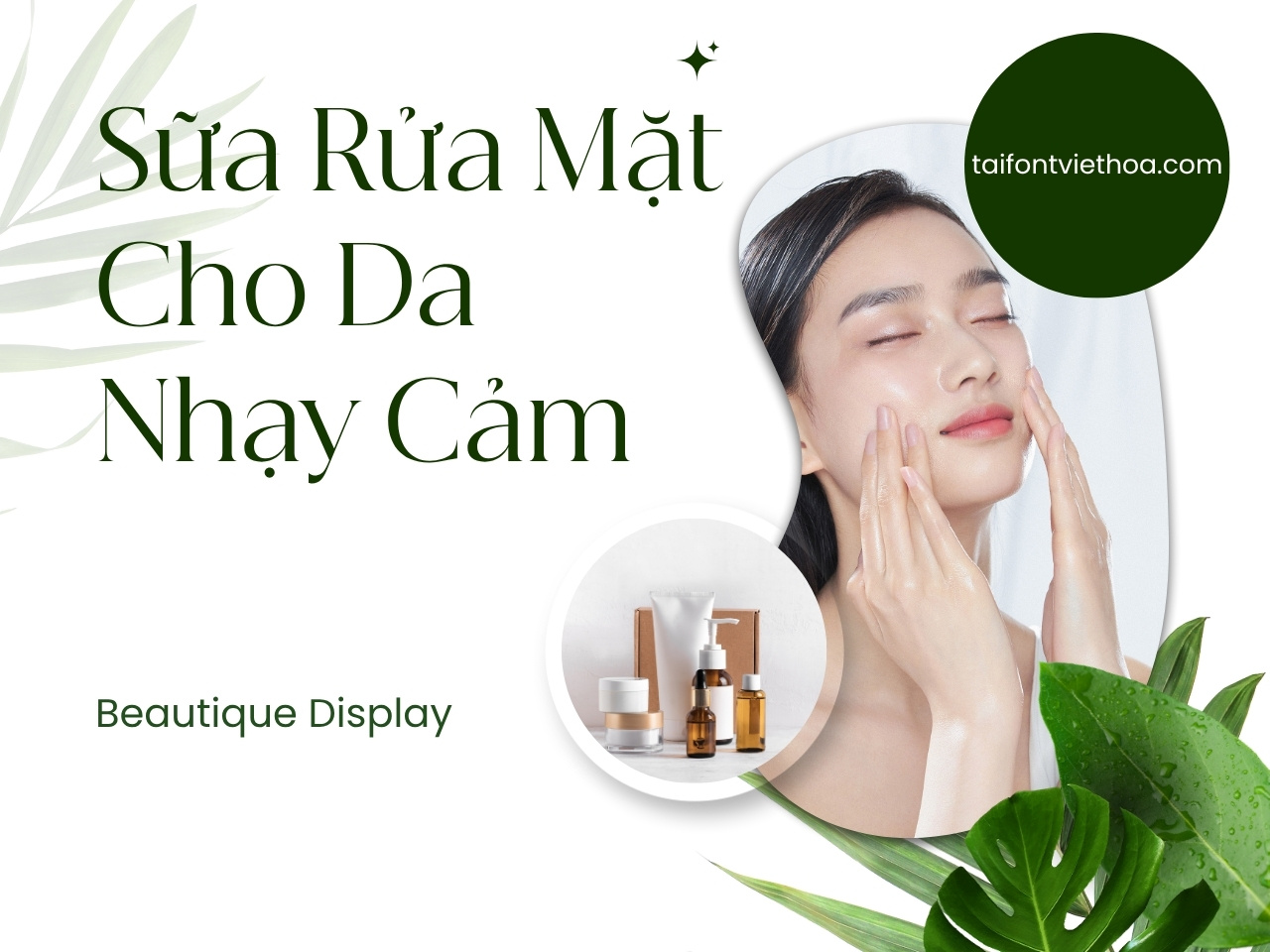
Giới thiệu về font Beautique Display 1.1 và phiên bản Việt hóa
Beautique Display 1.1 là bản mở rộng nâng cao từ font Beautique Display – một thiết kế serif tinh xảo được phát triển bởi Beautype Studio. So với bản đầu tiên, phiên bản 1.1 được tinh chỉnh lại tỷ lệ chữ, mở rộng thêm bộ glyphs đặc biệt, đồng thời cải thiện khả năng hiển thị trên các thiết bị kỹ thuật số và in ấn. Font vẫn giữ được nét sang trọng vốn có, nhưng tinh tế hơn và tối ưu hơn cho hệ thống thương hiệu chuyên nghiệp.
Bản Việt hóa do Beautype Studio trực tiếp thực hiện, hỗ trợ đầy đủ tiếng Việt có dấu và hơn 60 ngôn ngữ khác thuộc hệ Latin mở rộng. Font này sau đó được taifontviethoa.com kiểm duyệt và chia sẻ tới cộng đồng, như một phần trong bộ sưu tập font chữ cao cấp, giúp các nhà thiết kế tại Việt Nam có thêm lựa chọn hoàn hảo cho các dự án đặc thù về hình ảnh thương hiệu và truyền thông quảng cáo.
Đặc trưng thiết kế và phạm vi ứng dụng của Beautique Display 1.1
Beautique Display 1.1 vẫn giữ cấu trúc serif cổ điển nhưng tinh chỉnh một số chi tiết như độ mở của chữ, khoảng cách chữ cái và chiều cao chữ, mang lại cảm giác chuyên nghiệp và cân bằng. Đặc biệt, font cung cấp thêm các ligature độc quyền, các ký tự hoa cách điệu hỗ trợ tạo điểm nhấn trong thiết kế logo, tiêu đề hoặc ấn phẩm quảng cáo mang tính thương hiệu cá nhân.
Font này phù hợp với các ứng dụng trong ngành thời trang, mỹ phẩm, thiết kế thiệp cưới, bao bì sản phẩm cao cấp, website thương hiệu hoặc các sản phẩm truyền thông hình ảnh. Với độ thanh lịch và hiện đại trong từng đường nét, Beautique Display 1.1 giúp nâng tầm đẳng cấp thương hiệu ngay từ cái nhìn đầu tiên.